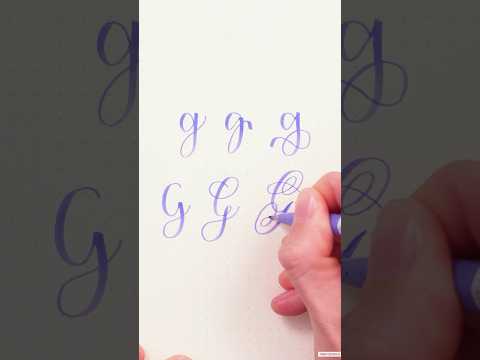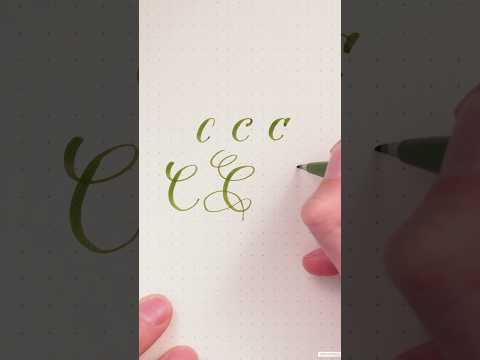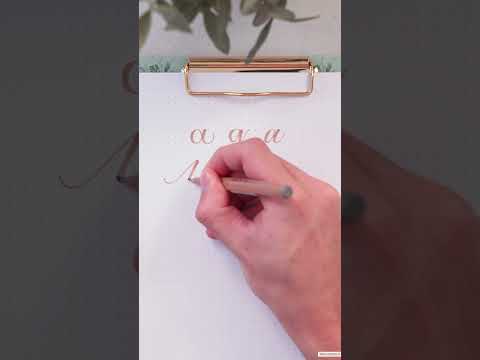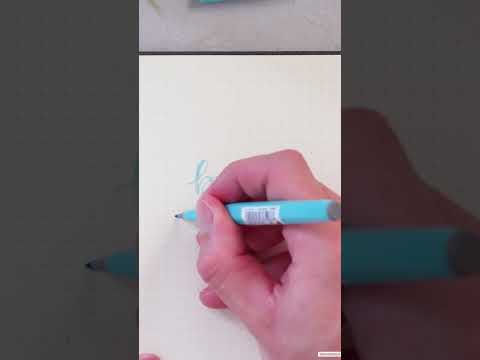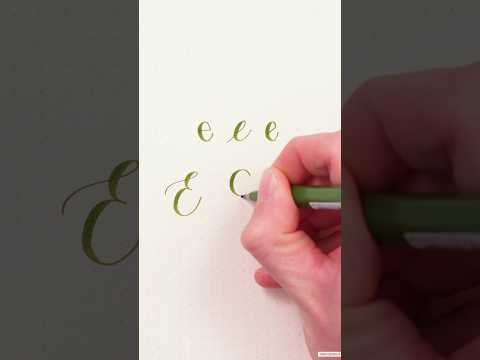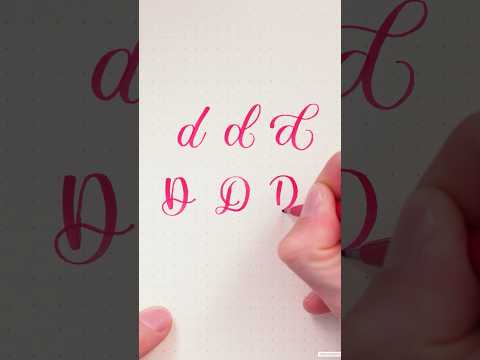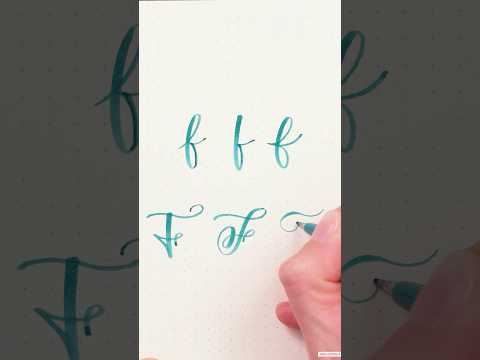
Handlettering Buchstaben kann man nie genug haben, richtig? Daher findest du hier eine kostenlose Buchstaben Sammlung. Dabei habe ich verschiedene Hand- und Brushlettering Varianten für dich gesammelt.
Es geht in diesem Fall nicht darum, immer die gleichen Stile für jeden Buchstaben aufzulisten, sondern eine gewisse Varianz zu erreichen. So kannst du die verschiedenen Stile selbst auf andere Buchstaben aus dem Alphabet übertragen.
Möchtest du hingegen komplette Alphabete für jeden Stil haben ist das ultimative Handlettering Alphabet die richtige Lösung.
Handlettering Buchstaben-Sammlung
Die folgende Übersicht enthält alle 26 Buchstaben unseres Alphabets – viel Spaß beim stöbern und entdecken. Per Klick auf ein Buchstaben-Set gelangst du zur Detail-Seite mit spannenden Informationen zu dem jeweiligen Buchstaben.
Buchstaben mit dem Brushpen
Für den Einsatz eines Brushpens habe ich eine weitere Sammlung gestartet. Hier bekommst du für jeden Buchstaben einige Variationen, sodass dein Repertoire an Stilen weiter wächst.
Zwischen Schreiben und Zeichnen
Beim Handlettering bewegen wir uns ganz oft zwischen dem Schreiben und dem Zeichnen. Genau das ist auch bei dieser Buchstaben-Sammlung der Fall.
Während der Buchstabe in einem bestimmten Stil direkt mit einer fließenden Bewegung und einem Brushpen gezogen werden kann, benötigst du bei einem anderen Stil unter Umständen eine Skizze und mehrere Schritte für die Entstehung.
Genau dieses Wechselspiel aus Techniken macht das Handlettering so unfassbar spannend und kreativ. Du lernst beim Handlettering also nicht einfach nur schön zu schreiben, sondern entdeckst automatisch wichtige Bereiche der Kalligrafie und des Zeichnens.